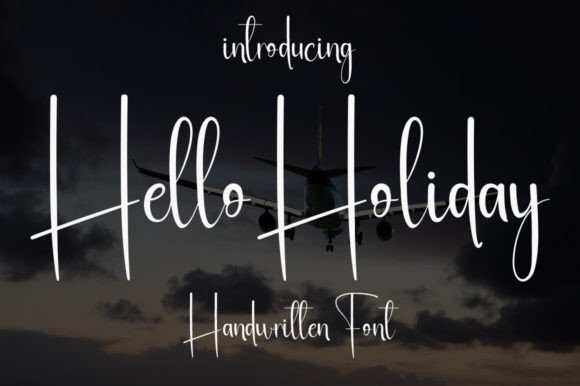
Hello Holiday
Descubra o Encanto do Hello Holiday: Uma Fonte Manuscrita Doce e Elegante
O Hello Holiday é uma fonte manuscrita doce e cursiva, criada para adicionar um toque de alegria e romance a seus projetos. Com sua forma gentil e suave, essa fonte é perfeita para uma variedade de ideias de design, desde convites de casamento até cartões de aniversário e muito mais.
Características do Hello Holiday
- Fonte manuscrita cursiva e doce
- Perfeita para projetos que exigem um toque de alegria e romance
- Pode ser usada em uma variedade de design, como convites, cartões e muito mais
O Hello Holiday é uma fonte versátil que pode ser usada em diferentes contextos, desde projetos pessoais até profissionais. Sua forma elegante e sofisticada torna-a perfeita para adicionar um toque de classe e sofisticação a seus designs. Além disso, sua natureza manuscrita a torna única e personalizada, o que é perfeito para projetos que exigem um toque humano.
Por Que Escolher o Hello Holiday?
Se você está procurando por uma fonte que possa adicionar um toque de alegria e romance a seus projetos, o Hello Holiday é a escolha perfeita. Com sua forma doce e cursiva, essa fonte é certa de impressionar e deixar uma marca duradoura em seus designs. Além disso, sua versatilidade e facilidade de uso a tornam uma escolha popular entre designers e criativos.